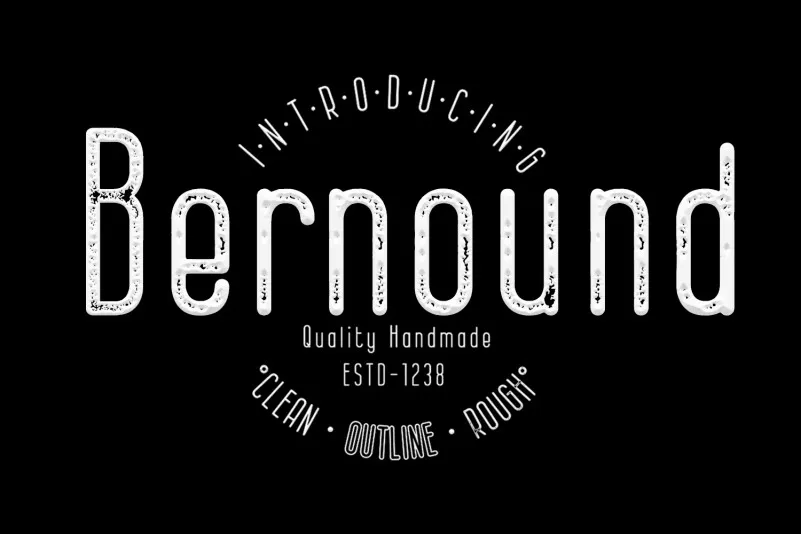
A ‘Bernound Font’ é uma excelente escolha para designers que procuram um tipo sem serif moderno e elegante. Oferecida em três pesos distintos, essa fonte tem uma aparência minimalista e clean, com linhas curvas e formas delgadas, criando uma atmosfera de simplicidade e beleza pura. O peso do traçado contornado destaca-se por sua elegância quando usada sozinha, enquanto o ‘peso marcado’ apresenta um toque vintage e rustic, fornecendo um contraste interessante com os outros pesos da família. Esta fonte oferece uma grande versatilidade para designers gráficos. Seu uso combinado permite criar designs únicos e imprevisíveis sem precisar adicionar mais fontes ou recursos digitais à sua base de software de design. Independentemente do estilo ou propósito de seu projeto, a ‘Bernound Font’ pode fornecer o toque final perfeito para qualquer layout ou arte digital. Escolha essa fonte moderna e versátil para dar um novo impulso ao seu trabalho de design.